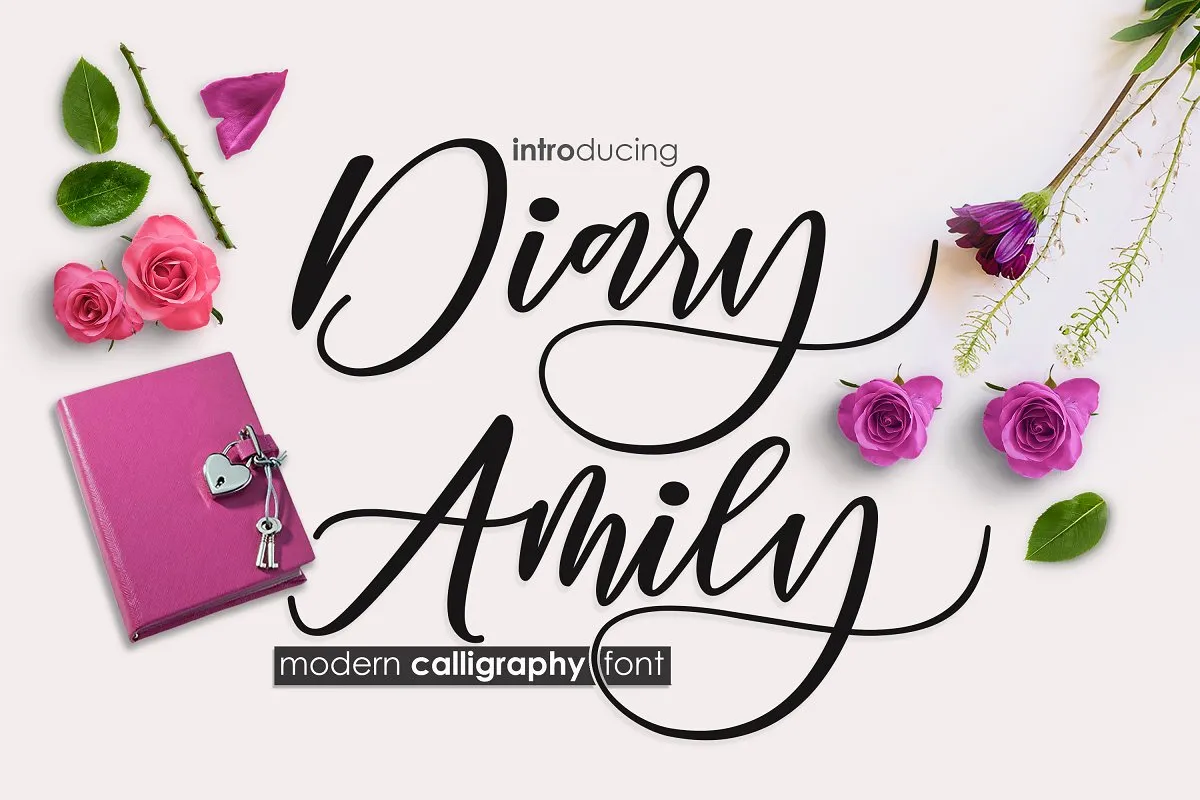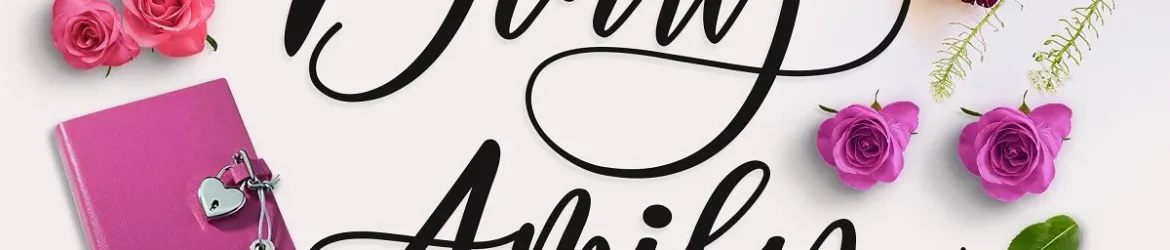
Diary Amily Script Font – Download Grátis
Diary Amily Script é uma nova adição ao catálogo das fuentes modernas de escrita à mão ligada. Inspirada por uma delicada entrada numa bela mulher, a fonte se destaca pela sua capacidade de criar trabalhos de escrita à mão impressionantes quando combinada com Stayland. Este design foi projetado para diversificar seu uso e agora se torna perfeito para inúmeras necessidades, como criações para marca, cartões de convite para casamentos, revistas, mugs, cartões de negócios, citações, panfletos e muitos outros elementos que você pode empregar em grandes projetos. A elegância deste script é algo a ser celebrado sempre que você desejar incluir uma escrita à mão moderna e sofisticada em seus trabalhos.